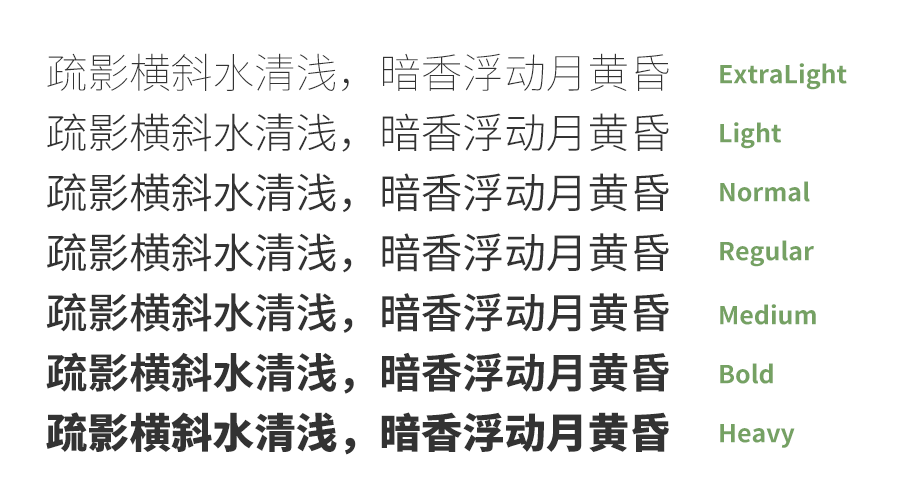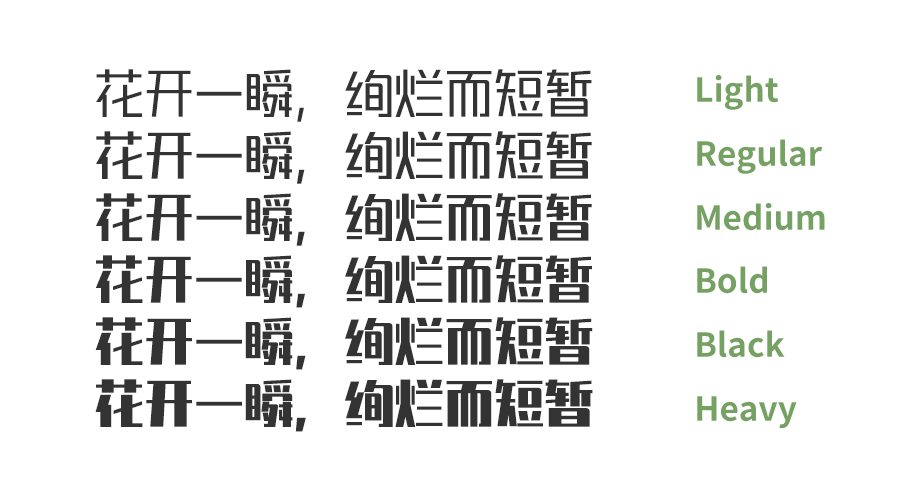
在设计领域,选择合适的字体如同为作品披上独特的外衣,能瞬间提升视觉吸引力。今天,为大家推荐两款免费且支持商用的家族字体,它们各具特色,能够满足不同设计场景的需求。
这款字体以其独特的笔触魅力脱颖而出,笔触浑厚有力,笔画曲折有度,展现出刚柔并济的美学平衡。字型个性鲜明,落笔简洁有序,给人以遒劲有力、端正凝练的第一印象。直角与圆角的巧妙结合,让字体在婉转中不失大方,每一笔一划都透露着设计者的匠心独运。提供6款丰富的字重选择,以及1款可变版,无论是标题还是正文,都能轻松驾驭,为设计作品增添无限创意与深度。
2.思源黑体 SC
作为开源字体界的佼佼者,思源黑体 SC由Adobe与Google强强联手,历经三年精心打磨而成,于2014年7月面世。它不仅覆盖了广泛的CJK(中文、日文、韩文)字符集,还提供了从ExtraLight到Heavy的七种粗细变化,满足不同阅读需求与视觉表达。其设计现代而均衡,既保持了黑体的清晰易读性,又融入了细腻的笔触变化,使得文字在不同尺寸下都能保持优美的视觉效果。对于追求高效、专业且注重跨平台一致性的设计师而言,思源黑体 SC无疑是理想之选。